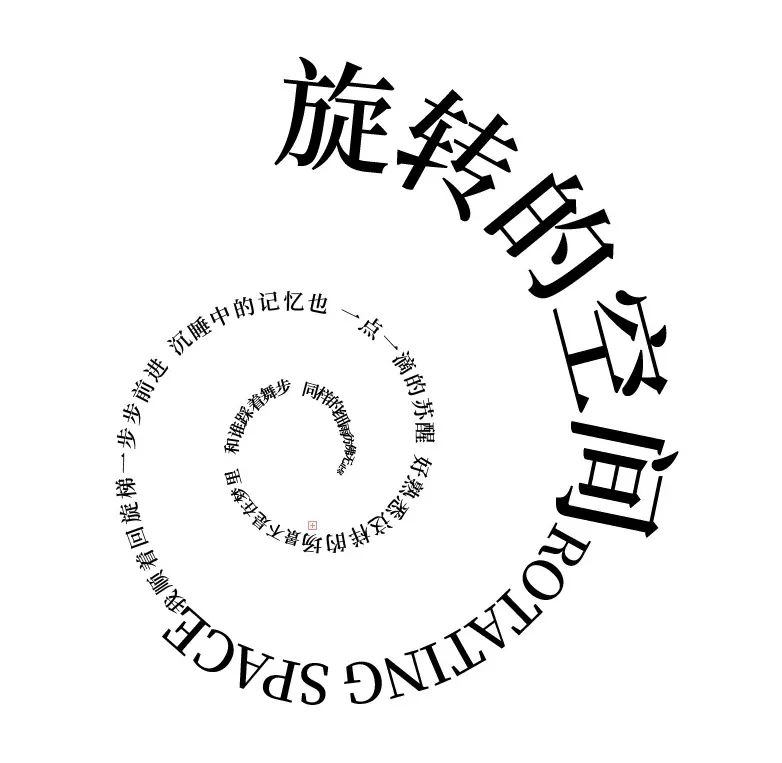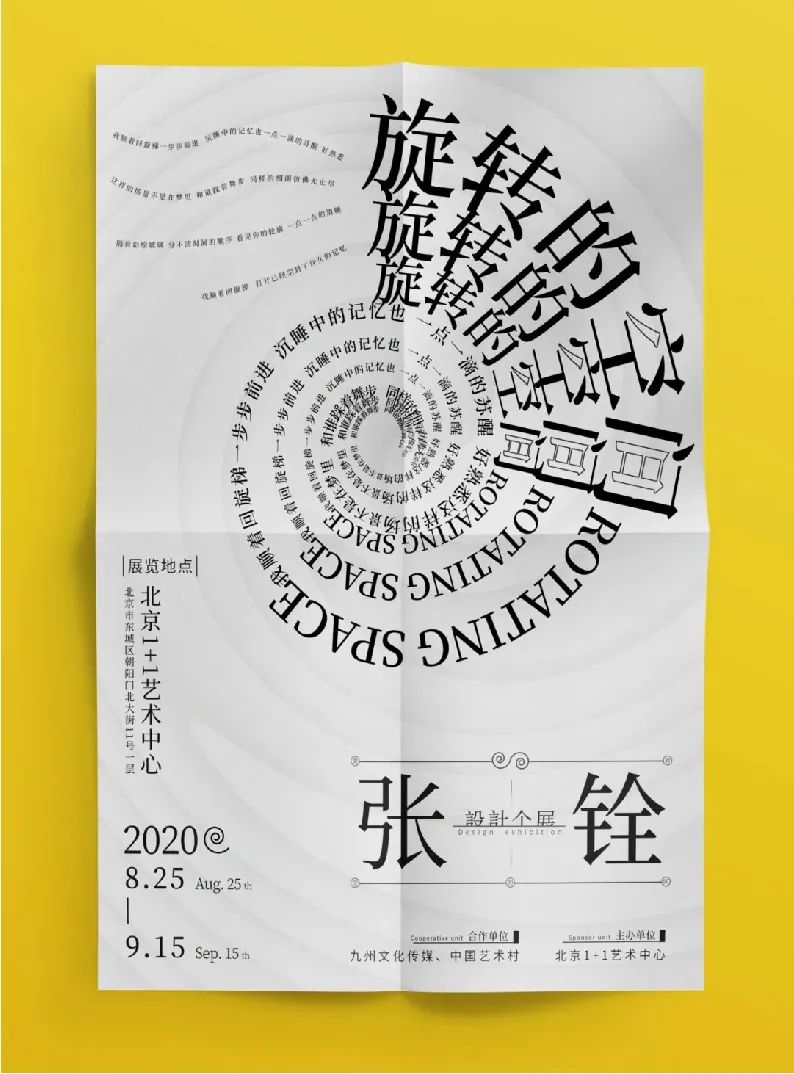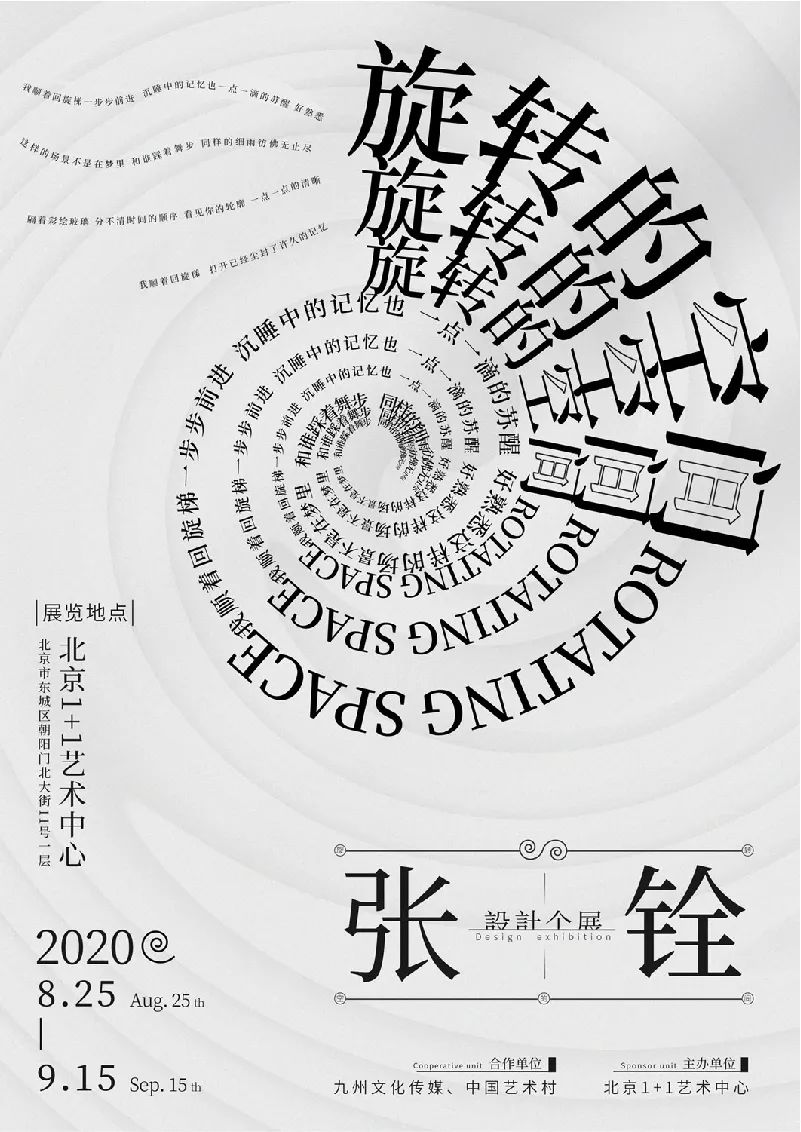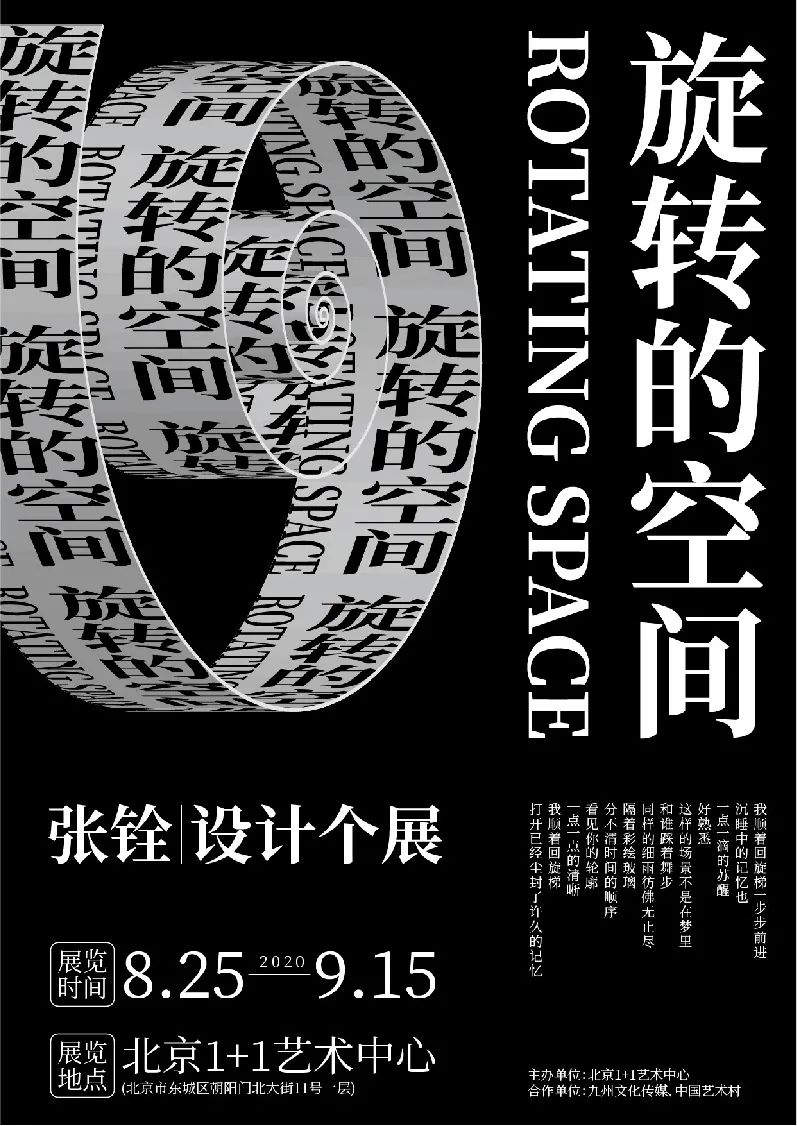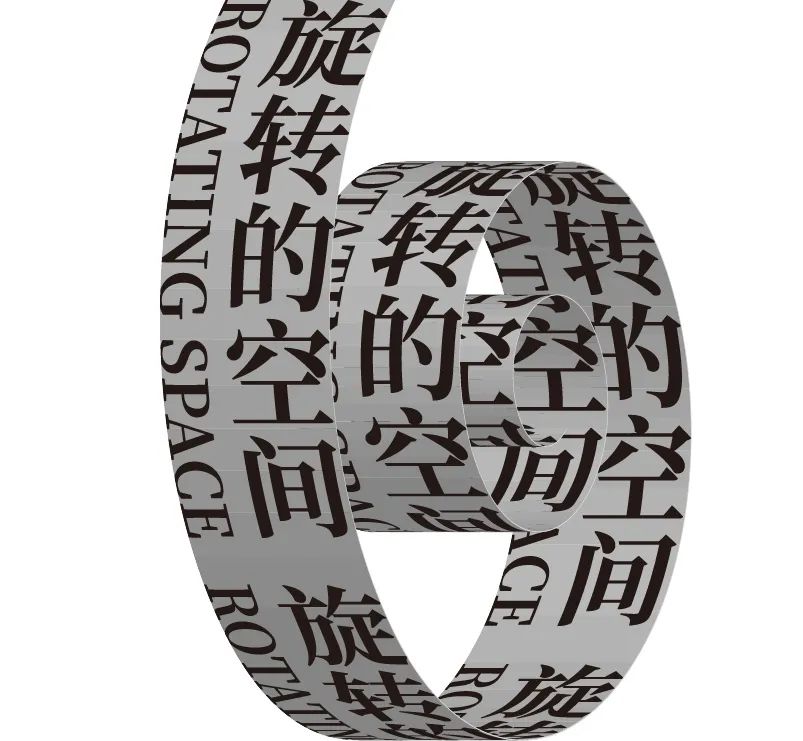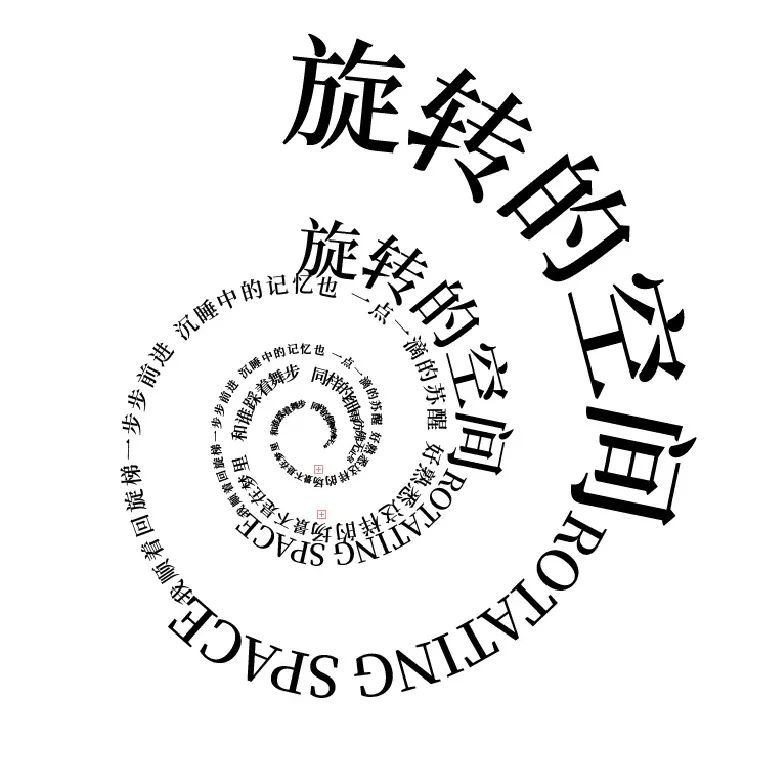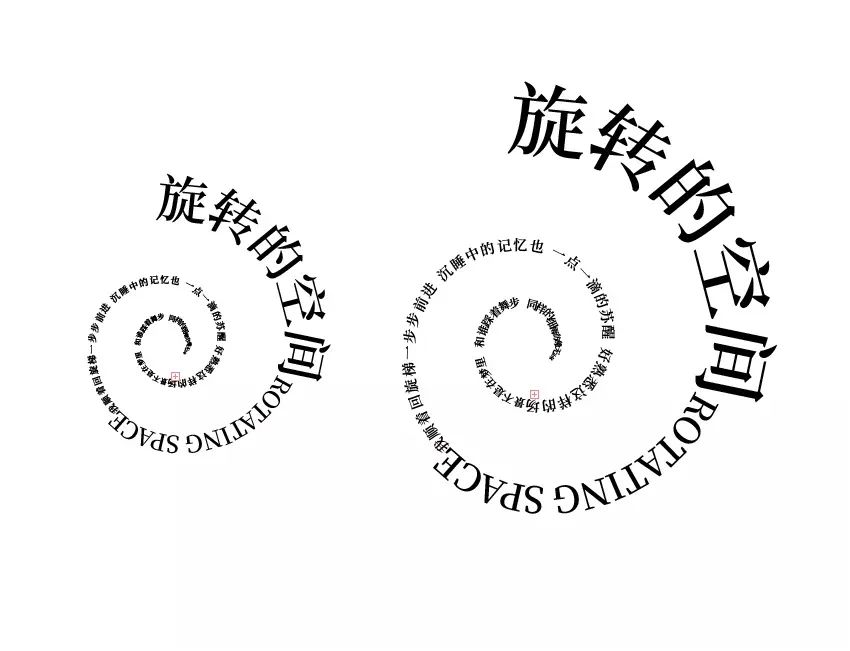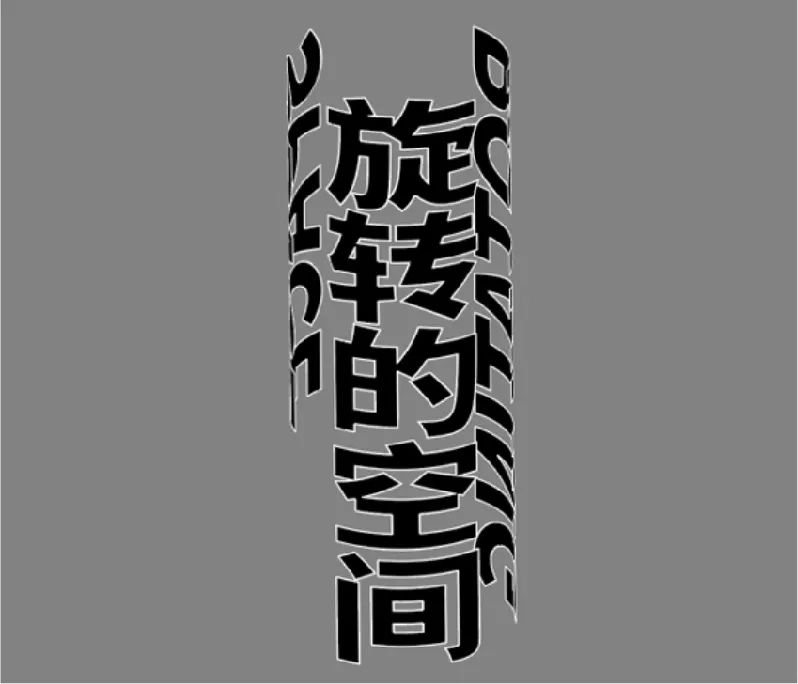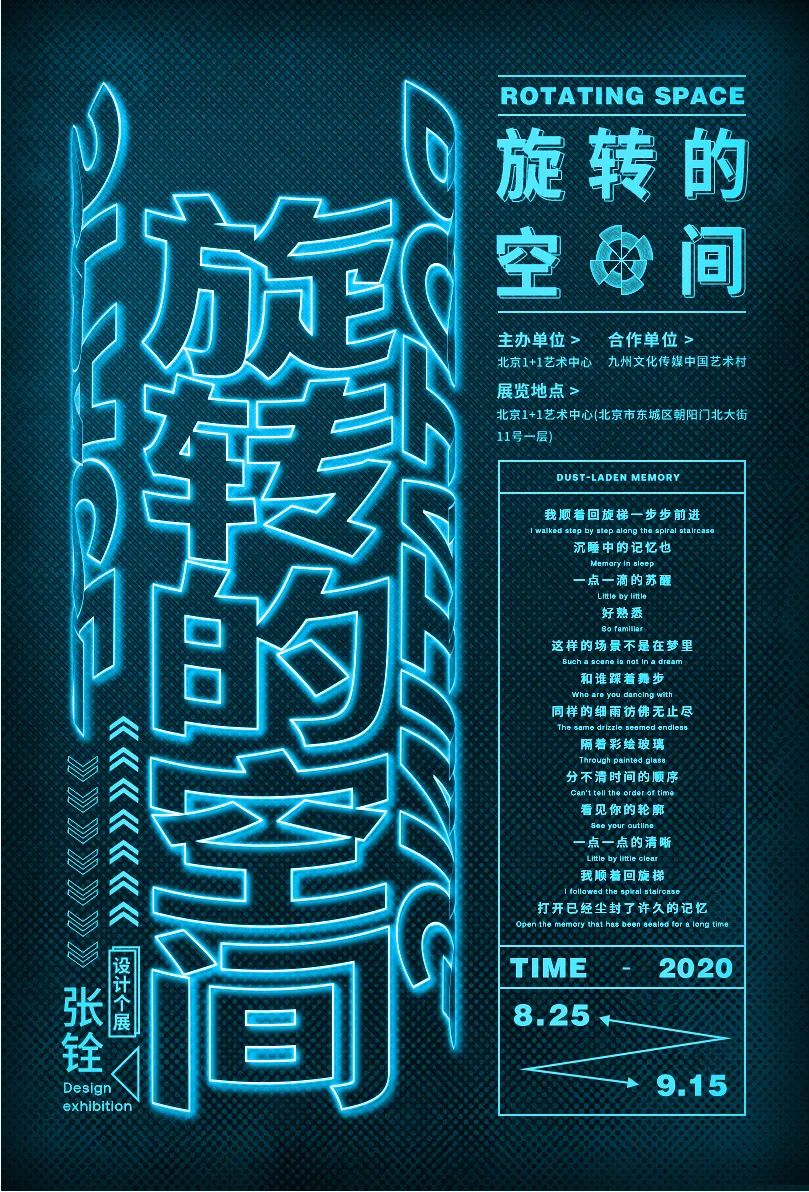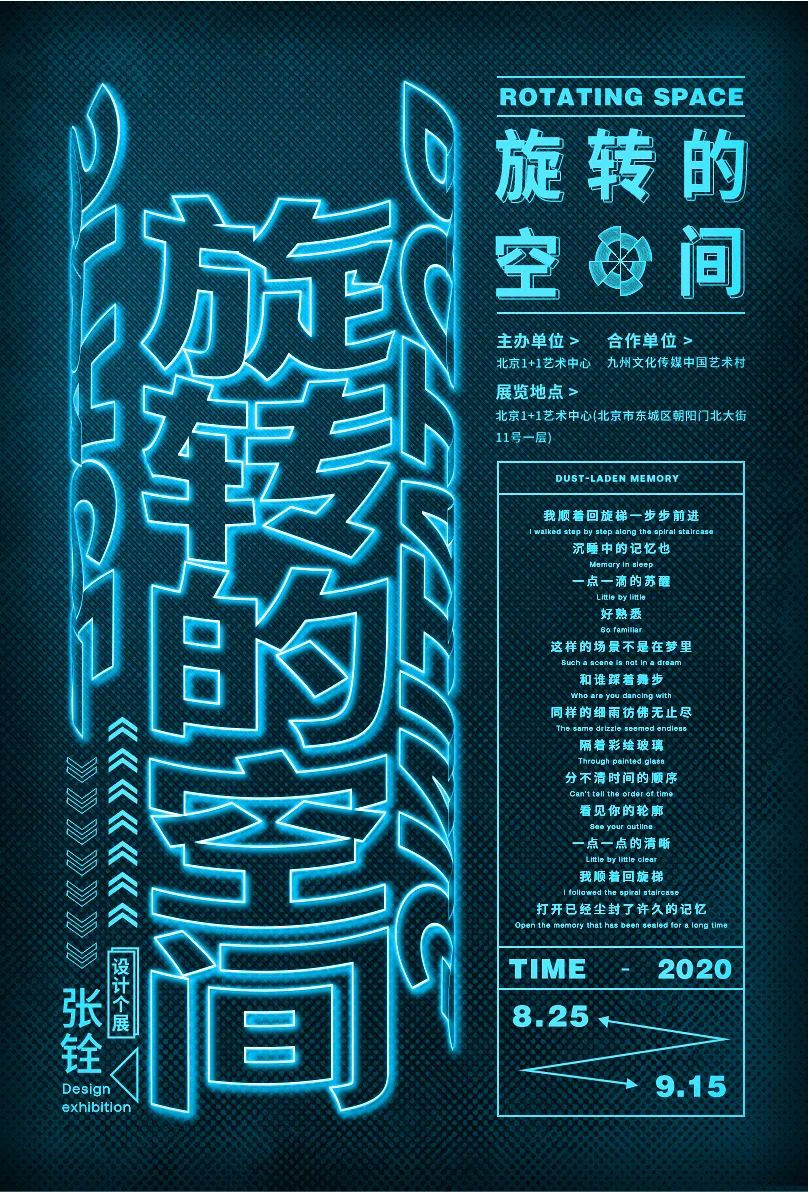
用三种方式,打开设计的旋转字体效果
今天分享三个开脑洞的旋转字体效果,没有C4D、AE高能加持,恰恰是你平时最熟悉的AI、PS,一起来学学吧。
1、使用【文字工具】输入主题文字“旋转的空间”,选择“对象”-“扩展”,再把文字逆时针旋转90°;3、选择【螺旋线工具】,描边为1,颜色选择白色,填充为0,画出右图的螺旋线;4、执行“效果”-“3D凸出及斜角”,打开“预览”,参考左图数据,调整旋转角度及凸出厚度:5、继续“贴图”,选择之前新建的符号,表面选择第3个面,然后点击“缩放以适合”;2、使用【路径文字工具】选择螺旋起始位置输入文字,形成文字螺旋效果;4、选择制作好的螺旋文字,复制一个新螺旋文字,调整合适大小;6、可以复制多个螺旋文字,分别调整大小,构建出螺旋通道,最终效果:制作软件:Illustrator、Photoshop1、输入海报主题文字,按下方图示排列,并给文字加上白色描边效果;3、用【椭圆工具】绘制一个圆形,“效果”-“3D凸出及斜角”,打开预览,设置角度和突出厚度到合适数值:4、进入“贴图”,勾选“三维模型不可见”,选择之前新建的符号,表面选择第3个面,然后调整好图案大小和位置;5、点击确定返回上一菜单,不断调整角度和凸出厚度,得到想要的效果:6、接下来制作发光效果。将调整好的3D字体效果导入PS中,图层“混合模式”改为“滤色”;7、复制新的图层,给下方图层添加”图层样式”的“外发光”效果;8、复制有外发光的图层,再进行“高斯模糊”,模糊后再复制一层得到最终效果:9、最后根据版面需要,调整背景颜色,加入文字信息: